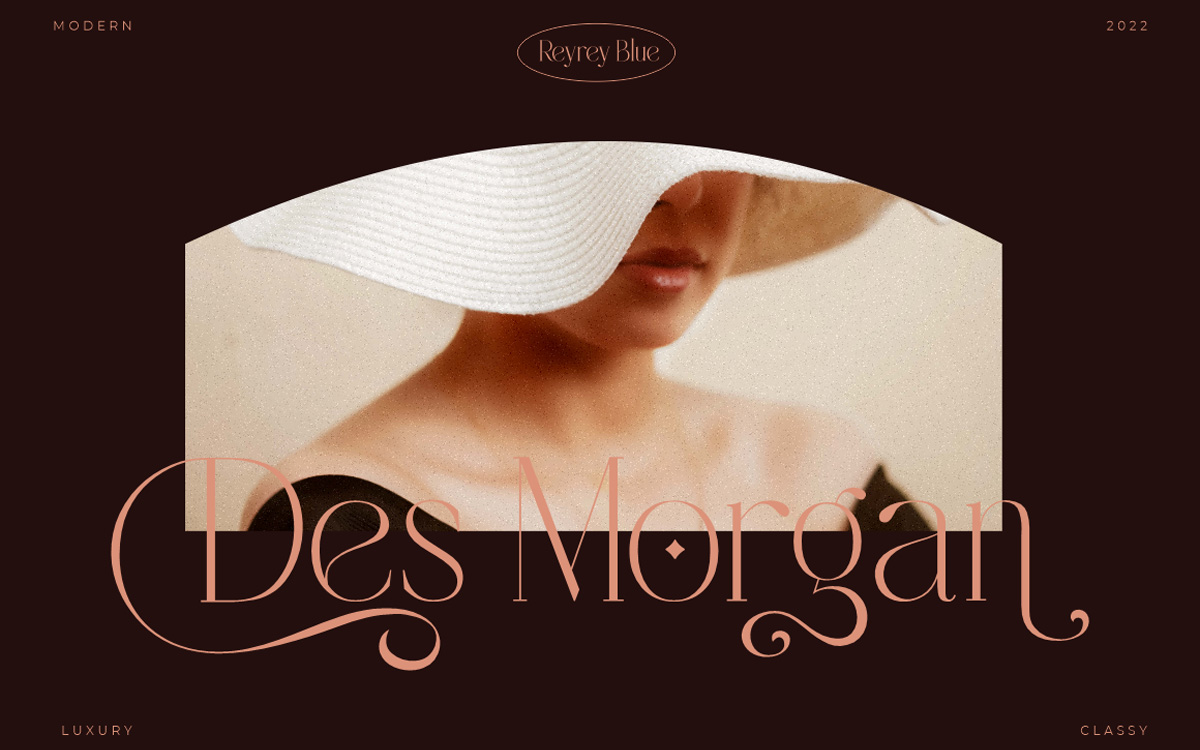
Font chữ thanh lịch, hiện đại, sang trọng dùng cho thiết kế thiệp cưới, thời trang, tạp chí TH Des Morgan
Trong thế giới thiết kế đồ họa cao cấp, việc lựa chọn một bộ font chữ phù hợp đóng vai trò tiên quyết trong việc định hình phong cách và nâng tầm giá trị cho toàn bộ ấn phẩm. Font chữ TH Des Morgan ra đời như một giải pháp hoàn hảo, mang đến sự hòa quyện tinh tế giữa nét cổ điển quý phái và tinh thần hiện đại thời thượng. Với phiên bản Việt hóa chỉn chu, TH Des Morgan hứa hẹn sẽ khai phóng nguồn cảm hứng sáng tạo vô tận cho các nhà thiết kế trong nhiều lĩnh vực nghệ thuật khác nhau.
Bộ font này không chỉ đáp ứng khắt khe các tiêu chuẩn thẩm mỹ cao cấp mà còn giúp truyền tải thông điệp thương hiệu một cách trọn vẹn, đầy cảm xúc và quyến rũ.
Font chữ thanh lịch, hiện đại, sang trọng TH Des Morgan – Giải pháp Việt hóa đỉnh cao cho thiệp cưới, thời trang và tạp chí cao cấp
Font chữ TH Des Morgan là một trong những kiệt tác typography thuộc dòng Serif hiển thị (Display Serif), được thiết kế tỉ mỉ để tôn vinh sự quý phái và nét đẹp tân tiến. Từng đường nét của font chữ đều chứa đựng sự tính toán kỹ lưỡng về mặt thị giác, đem lại sự cân bằng hoàn hảo giữa độ tương phản nét thanh nét đậm. Khi ứng dụng vào các ấn phẩm truyền thông hay thiết kế thương hiệu, TH Des Morgan lập tức tạo nên một dấu ấn đậm chất thượng lưu, giúp tác phẩm của bạn nổi bật hoàn toàn so với các thiết kế thông thường.
1. Phong cách Serif hiện đại kết hợp đường nét uốn lượn tinh tế
Cấu trúc chữ của TH Des Morgan dựa trên nền tảng của font Serif truyền thống nhưng đã được cách điệu táo bạo với những đường cong mềm mại và chân chữ gọn gàng. Độ tương phản cao giữa nét chính và nét phụ tạo nên nhịp điệu thị giác vô cùng cuốn hút. Ngoài ra, font chữ còn sở hữu hệ thống ký tự thay thế (alternates) và ký tự nối (ligatures) vô cùng phong phú, cho phép người dùng tự do biến tấu các tiêu đề trở nên độc bản và nghệ thuật hơn.
2. Bộ ký tự Việt hóa hoàn chỉnh, tối ưu hóa hiển thị tiếng Việt
Một ưu điểm vượt trội của TH Des Morgan chính là bản Việt hóa đầy đủ và chuẩn xác từng chi tiết. Các dấu thanh tiếng Việt (huyền, sắc, hỏi, ngã, nặng, dấu mũ, dấu móc) được thiết kế đồng điệu hoàn toàn với nét chữ gốc về góc nghiêng, độ dày và tỷ lệ khoảng cách. Điều này giải quyết triệt để tình trạng lỗi font hay dấu thanh bị thô cứng, giúp các câu văn tiếng Việt khi trình bày vẫn giữ nguyên vẻ mượt mà, thanh thoát và đạt tính thẩm mỹ tối đa.
3. Ứng dụng đỉnh cao trong thiết kế thiệp cưới và sự kiện lãng mạn
Thiệp cưới là nơi lưu giữ những khoảnh khắc hạnh phúc nhất của đôi lứa, yêu cầu tính nghệ thuật và sự lãng mạn cao. Font chữ TH Des Morgan với nét đẹp thanh lịch và quý phái là lựa chọn hàng đầu cho các nhà thiết kế thiệp cưới cao cấp. Từ tên chú rể cô dâu trên thiệp mời, thiệp báo hỷ, sơ đồ bàn tiệc đến các loại thẻ cảm ơn, font chữ này đều tỏa sáng rực rỡ. Khi được kết hợp với các kỹ thuật in ấn như ép kim (foil stamping), dập nổi (embossing) trên chất liệu giấy mỹ thuật cao cấp, TH Des Morgan sẽ biến tấm thiệp cưới thành một tác phẩm nghệ thuật sang trọng.
4. Lựa chọn lý tưởng cho ngành thời trang, mỹ phẩm và nhận diện thương hiệu
Trong phân khúc thời trang cao cấp, mỹ phẩm xa xỉ và các thương hiệu hàng hiệu, hình ảnh nhận diện luôn đòi hỏi sự tinh tế và đẳng cấp vượt thời gian. TH Des Morgan thể hiện xuất sắc vai trò của mình khi được áp dụng vào thiết kế logo, nhãn mác sản phẩm, bao bì mỹ phẩm, bảng hiệu boutique hay brochure bộ sưu tập mới. Nhờ vẻ ngoài vừa thanh lịch vừa hiện đại, font chữ này giúp các thương hiệu dễ dàng định vị phân khúc cao cấp và thu hút đối tượng khách hàng thượng lưu.
5. Tối ưu cho thiết kế tạp chí, bìa sách và ấn phẩm truyền thông số
Không chỉ mạnh mẽ trong thiết kế thương hiệu và in ấn nghệ thuật, TH Des Morgan còn là giải pháp tuyệt vời cho mảng dàn trang tạp chí (editorial design), thiết kế bìa sách, poster triển lãm hay banner truyền thông trên nền tảng số. Việc sử dụng TH Des Morgan cho các dòng tiêu đề lớn (headlines) hay các câu dẫn ấn tượng (quotes) sẽ tạo ra điểm nhấn thị giác mạnh mẽ, dẫn dắt ánh nhìn của người đọc và tạo nên bố cục tổng thể vô cùng chuyên nghiệp, hiện đại.
Bí quyết phối hợp font chữ TH Des Morgan tạo nên tác phẩm chuẩn mỹ thuật
Để phát huy tối đa sức mạnh thẩm mỹ của TH Des Morgan trong các dự án thiết kế, nhà thiết kế có thể áp dụng những nguyên tắc phối chữ chuẩn chuyên nghiệp sau:
• Kết hợp cùng font Sans-Serif tối giản: Đối với phần văn bản nội dung dài (body text), hãy phối hợp tiêu đề TH Des Morgan với các bộ font Sans-serif đơn giản như TH Inter, Montserrat hoặc Helvetica để tạo ra sự tương phản rõ rệt, vừa nâng cao tính thẩm mỹ vừa đảm bảo khả năng đọc dễ dàng.
• Khai thác tối đa bảng ký tự Glyphs: Bật bảng tính năng Glyphs trong Adobe Illustrator, Photoshop hoặc InDesign để lựa chọn các ký tự biến thể và nét nối lượn sóng độc đáo cho các từ khóa quan trọng trong logo hay tiêu đề thiệp cưới.
• Tăng khoảng cách chữ (Tracking) cho dòng chữ viết hoa: Khi sử dụng TH Des Morgan ở định dạng viết hoa toàn bộ (ALL CAPS) cho các tiêu đề ngắn, hãy tăng khoảng cách giữa các ký tự nhẹ nhàng để tạo cảm giác thoáng đãng, sang trọng và mang đậm phong cách tạp chí thời trang Châu Âu.